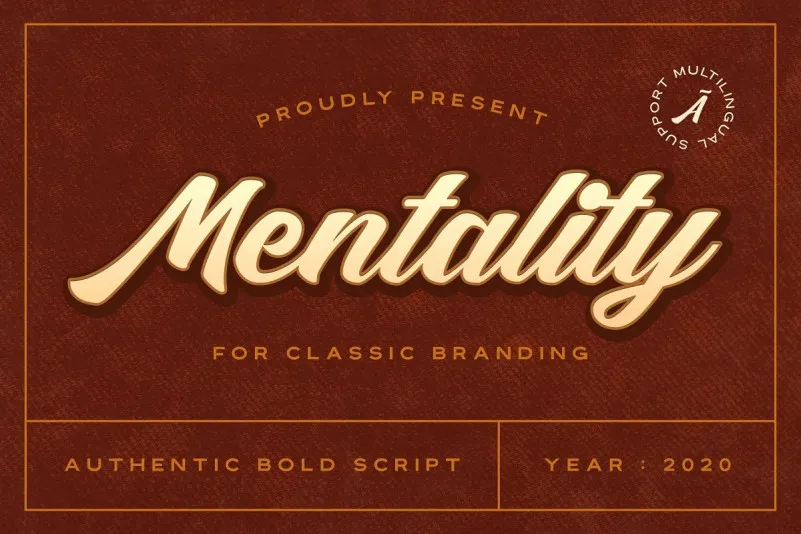
A Mentality Font é uma escolha perfeita para os criadores que buscam adicionar um toque autêntico ao seu trabalho visual sem comprometer a elegância e robustez do design moderno. Esta tipografia script bold traz consigo o charme de uma escrita à mão, repleta de vida e beleza vintage, projetada para destacar qualquer logotipo ou identidade visual. Ideal tanto para aplicação em logotipos quanto em selos e rótulos, a Mentality Font é inspirada no movimento artístico e arquitetônico decorativo, oferecendo uma textura única que remete a tempos passados enquanto mantém um olhar contemporâneo. Seja ela usada como logotipo de marca, em selos personalizados ou até mesmo rótulos de produtos, esta fonte certamente tornará seu design mais interessante e diferenciado. Perfeita para designers que buscam uma mistura arrebatadora entre antiguidade e modernidade, a Mentality Font é uma opção irresistível se você está procurando um pouco mais do que o básico. Sem dúvida, ela será um grande complemento para qualquer projeto gráfico onde um toque vintage seja bem-vindo.